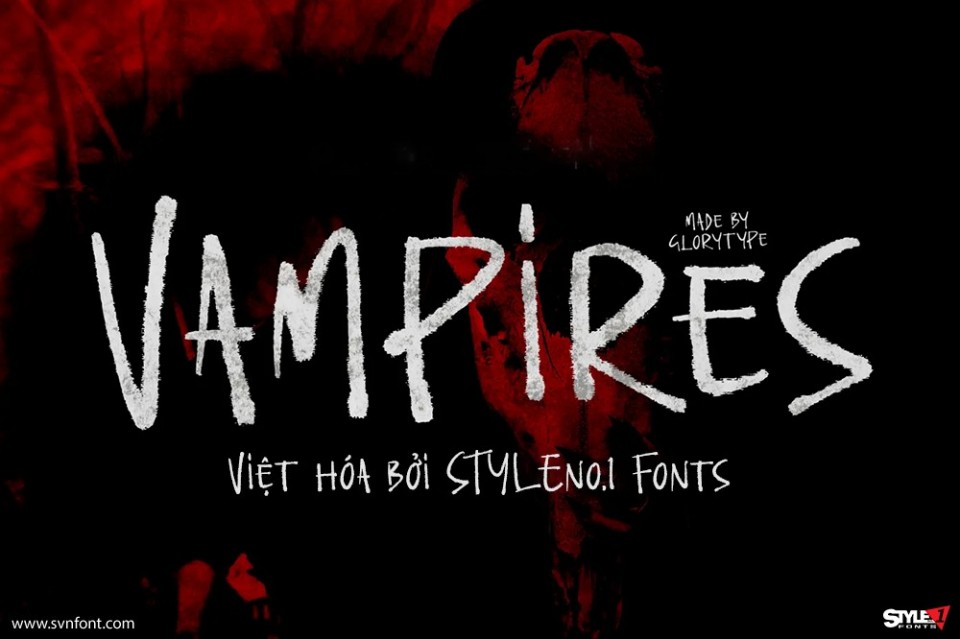
Font việt hóa SVN Vampires
Font việt hóa SVN Vampires – Bộ Font Chữ Nghệ Thuật Độc Đáo Cho Thiết Kế
Trong thế giới thiết kế đồ họa, việc lựa chọn một Font Miễn Phí chất lượng là yếu tố then chốt để tạo nên linh hồn cho tác phẩm. Font việt hóa SVN Vampires nổi lên như một lựa chọn hàng đầu dành cho các nhà thiết kế đang tìm kiếm phong cách ma mị, huyền bí và đầy sức hút. Được tùy chỉnh kỹ lưỡng về dấu tiếng Việt, bộ font này giúp các bạn học sinh và sinh viên dễ dàng trình bày bài thuyết trình hoặc dự án cá nhân mà không lo lỗi hiển thị.
Khám phá sức hút của Font việt hóa SVN Vampires
Bộ font này mang đậm hơi hướng Gothic cổ điển với những đường nét sắc sảo, thanh mảnh nhưng vô cùng mạnh mẽ. Font việt hóa SVN Vampires thường được sử dụng trong các bối cảnh đòi hỏi sự sáng tạo cao như bìa sách, poster phim kinh dị hoặc các thiệp mời sự kiện chủ đề Halloween. Sự cân bằng giữa tính thẩm mỹ và khả năng đọc hiểu giúp nó trở nên linh hoạt trong nhiều định dạng khác nhau.
Ứng dụng thực tế trong học tập và sáng tạo
Đối với môi trường học đường, các bạn có thể dùng font này để thiết kế tiêu đề cho các tờ báo tường hoặc trang trí tập san lớp. Những nét chữ uốn lượn đặc trưng sẽ giúp nội dung trở nên nổi bật và gây ấn tượng mạnh với người xem ngay từ cái nhìn đầu tiên. Ngoài ra, tính năng việt hóa chuẩn giúp các ký tự có dấu trông tự nhiên và hài hòa với tổng thể bộ chữ.
Lưu ý khi sử dụng Font việt hóa SVN Vampires
Dù sở hữu vẻ ngoài bắt mắt, người dùng nên lưu ý kết hợp Font việt hóa SVN Vampires với các font chữ không chân đơn giản để đảm bảo bố cục không bị rối mắt. Việc phân cấp nội dung rõ ràng sẽ giúp thông điệp truyền tải hiệu quả hơn. Hy vọng rằng với sự hỗ trợ từ Font Miễn Phí, Font Việt Hóa, Font việt hóa SVN Vampires, bạn sẽ có thêm nguồn cảm hứng để hoàn thành những sản phẩm thiết kế tuyệt vời nhất của mình.